акцидентний шрифт
"Особливі шрифти для особливих цілей" - це чи не визначення акцидентної шрифтів? У попередньому поколінні вони хизувалися чистої геометрією, алюзіями, романтичними мотивами. Нині в моді "забруднення", мотиви грубого шрифтового побуту, класичні форми, надіслані до абсурду.
- ШРИФТ - тіпогр. літери певного розміру і рис. для набору. Тип Ш. його форма і розміри в філат. мають певне значення при класифікації марок та ін. філат.
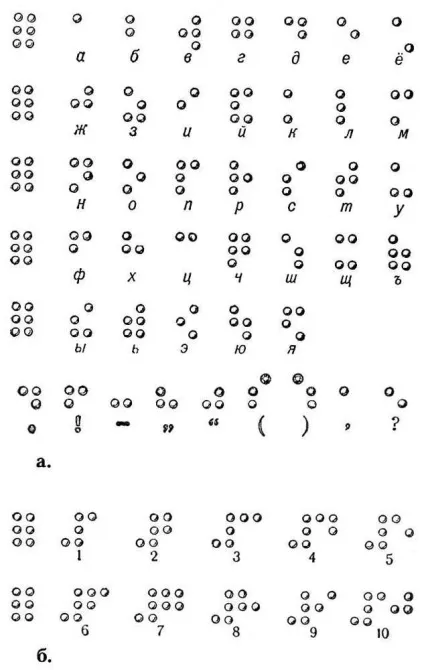
Брайля шрифт Брайля шрифт, рельєфно-крапковий шрифт для письма і читання сліпих, розроблений Л. Брайлем. В основі Б. ш. лежить комбінація шести точок. Брайль прийняв порядок букв латинського алфавіту. Для позначення перших букв алфавіту служать верхні і середні точки
Шрифт Шрифт (нім. Schrift, від schreiben - писати), графічна форма знаків алфавітної системи листи. Залежно від техніки відтворення Ш. розрізняють слід. його основні види: рукописний, написаний пером або іншим інструментами на м'якому матеріалі (папірусі, пергаменті,
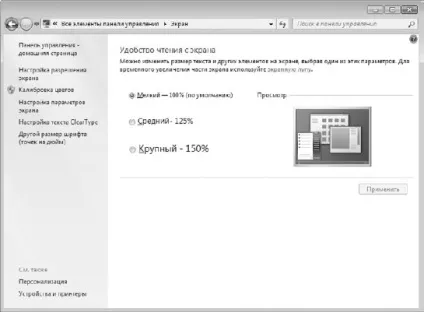
6.3. Шрифт Інформація, яка виводиться на екран монітора, відображається з використанням певного розміру шрифту. При цьому додатки, які використовують у своїй роботі системні шрифти, потрапляють під управління операційної системи і вона сама може регулювати
Шрифт Ви, швидше за все, бачили в різних документах Word, що одна і та ж буква на екрані може виглядати зовсім по-разному.Ітак, у букв є три найважливіших властивості, які ви можете змінювати в Word - шрифт, розмір і накреслення. Допоможуть вам у цьому інструменти групи Шрифт
КВАДРАТНИЙ ШРИФТ форма * древнеевр. листи, що з'явилася в останні століття до н.е. См.ПБЕ, т.9, с.303-06 і